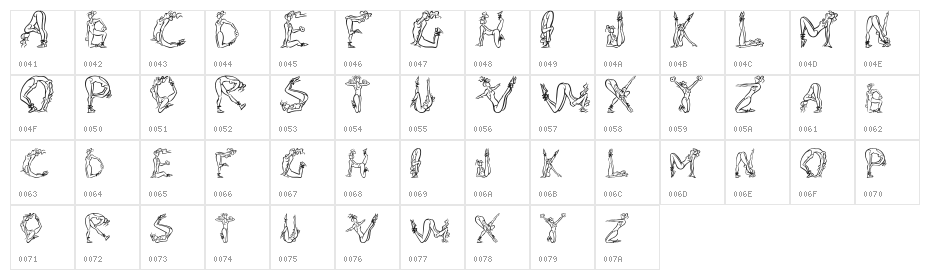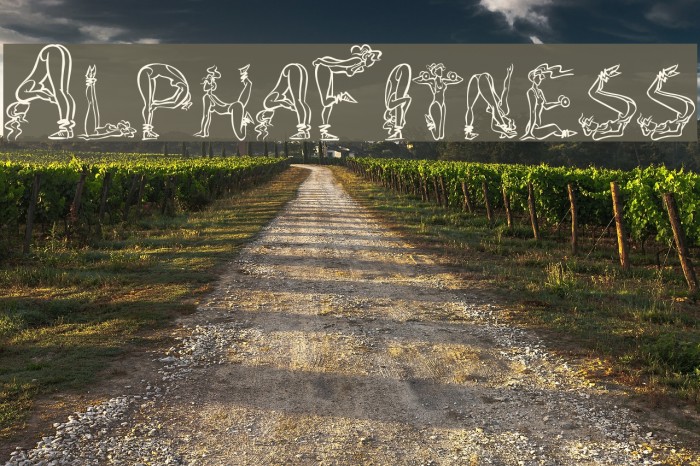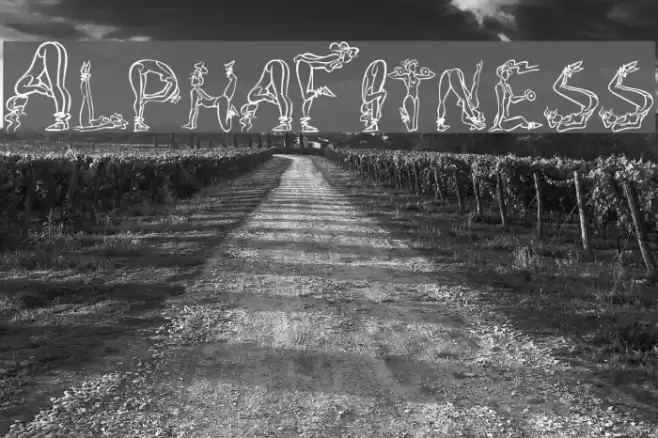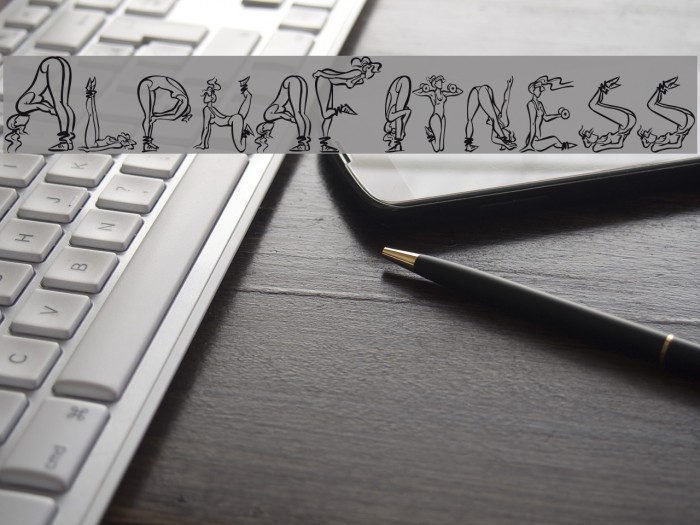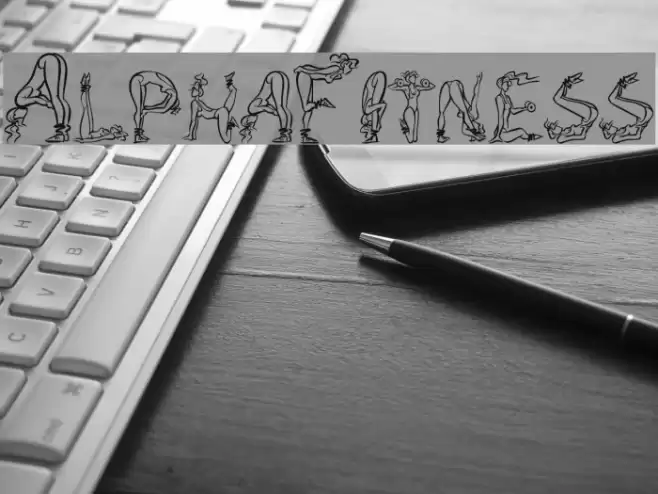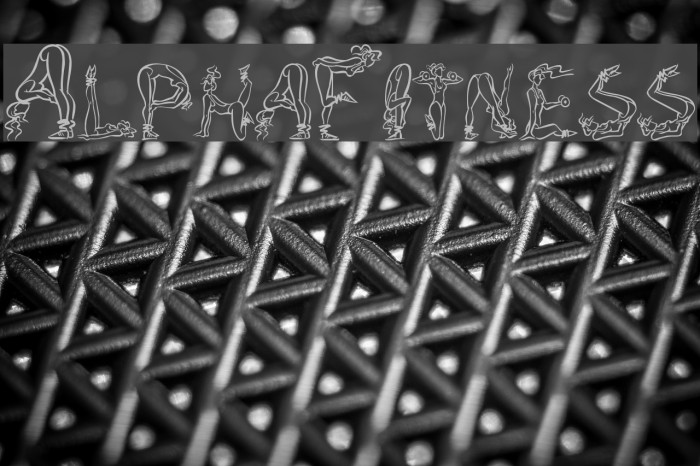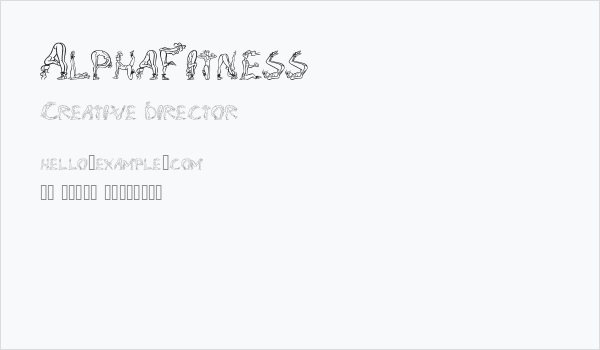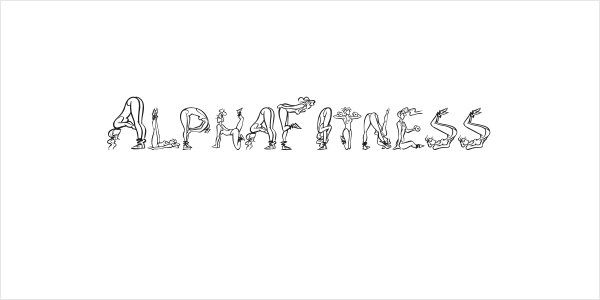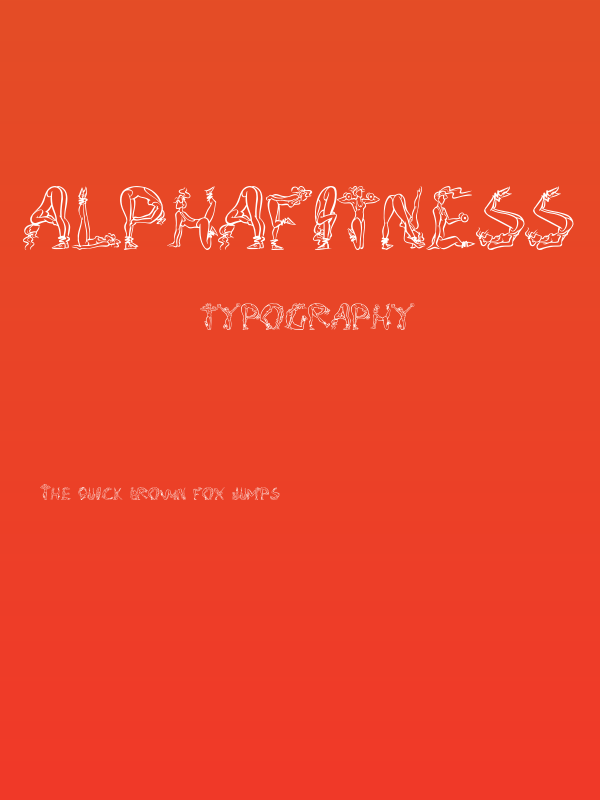
AlphaFitness Font
✎ Decorative
Diese Schriftart enthält 56 Zeichen. Klicken Sie auf ein Zeichen für Details.
| Anwendungsfall | Logos, Headlines, Posters |
| Vorgeschlagene Projekte | Ideal for fitness-related branding, sports event posters, or playful design projects. |